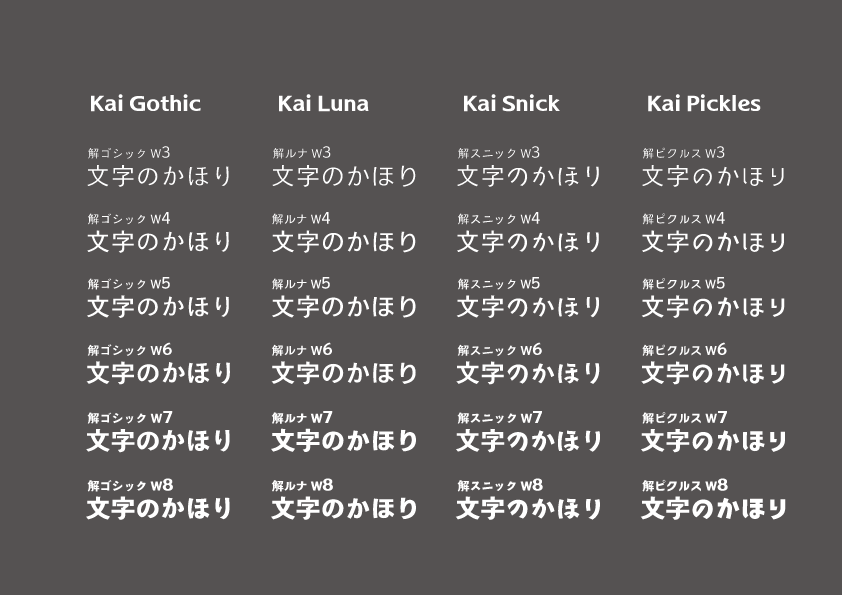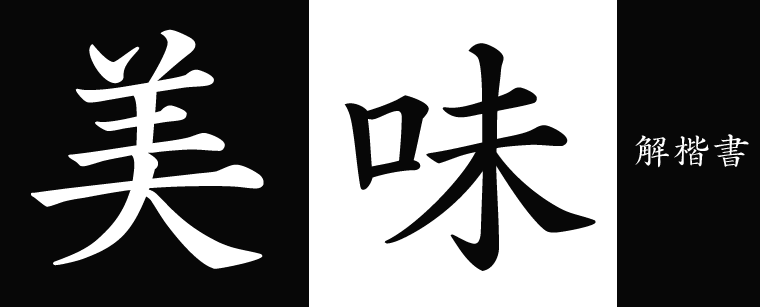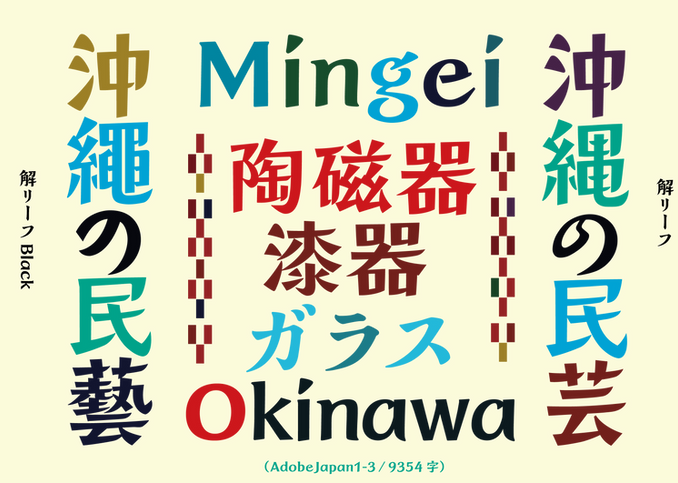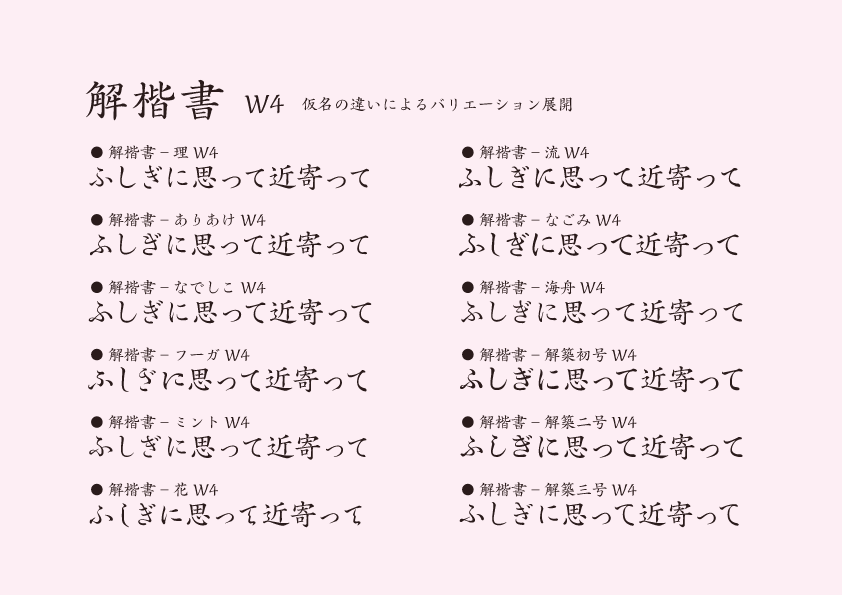
​解リーフ
​解ゴシック
•「 解ゴシック」は、活版時代の字形を継承したナチュナルで馴染みのある仮名です。文字字形のふところに配慮し組版の濃度バランスを整えました。目にも優しく判読性のよい組版になるとおもいます。
•「解ルナ」は、電子社会のヨコ組みに適した視覚的ラインを探し、モダンな表現形態を求めました。
二つの新しいエレメントはちらつきを抑えた曲線と明瞭な字形構成によって情報量の多い複雑な誌面に一定の秩序を与え、明解な誌面になると思います。
解ゴシックは2001年最初の制作を始めました。WEBなど電子機器モニターでの表示が多くなり、文字情報の電子化に備え明解な文字形体を探る必要を感じたのでした。
​解楷書 Family
●日本語文脈で漢字は主題目を示すことが多い。楷書は、私たちの潜在意識にしっかりとあり、漢字に楷書を用いることで潜在する可読性を呼び起こそうと試みた。​加えて、私たちのこまやかな心情を表現することができる仮名を多種類備えることで、本文組版に豊かなを多様性をもたせようとした。----仮名製品もじのかおりへ・・・
​解-仮名
漢字に楷書を用いることで潜在する可読性を呼び起こそうと試みました。その試みの中で・・
●もじのかおり
私たちのこまやかな心情を表現することができる仮名の豊かさを探しました。
◆W4・W5・W7を揃えたましたので、
解楷書・解星との合成フォントで使用いただける事と思います。
・解宙、モアリア、また他の明朝体にも、お試しいただけることを願っています。
Google Kaisei
解星対応仮名
● Google Fonts Kaisei  に合成して利用できる「仮名」を​準備いたしました。
W4, W5, W7,W8
● 解星は
​●「解星」は従来の明朝体の筆法とは異り、右払い・ハネにドット=星を配置しながら、偕法から離れる不安定さを補いました。漢字の横線は従来明朝体より太めの設定になっています。
導き出したこれらのエレメントはWEBにおいて明朝体の弱みである細い横線と払いの先端のチラツキを抑えます。